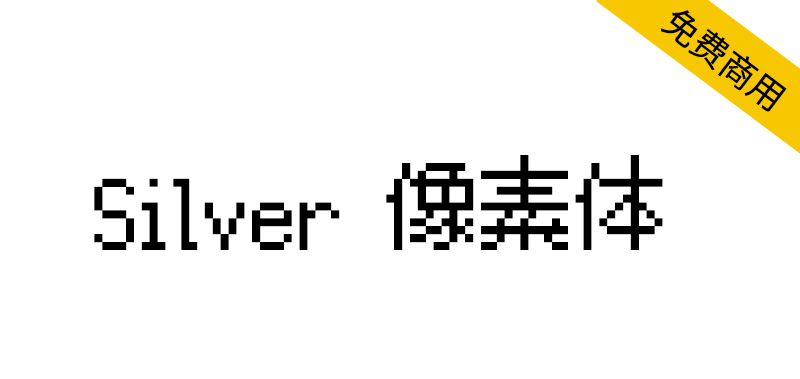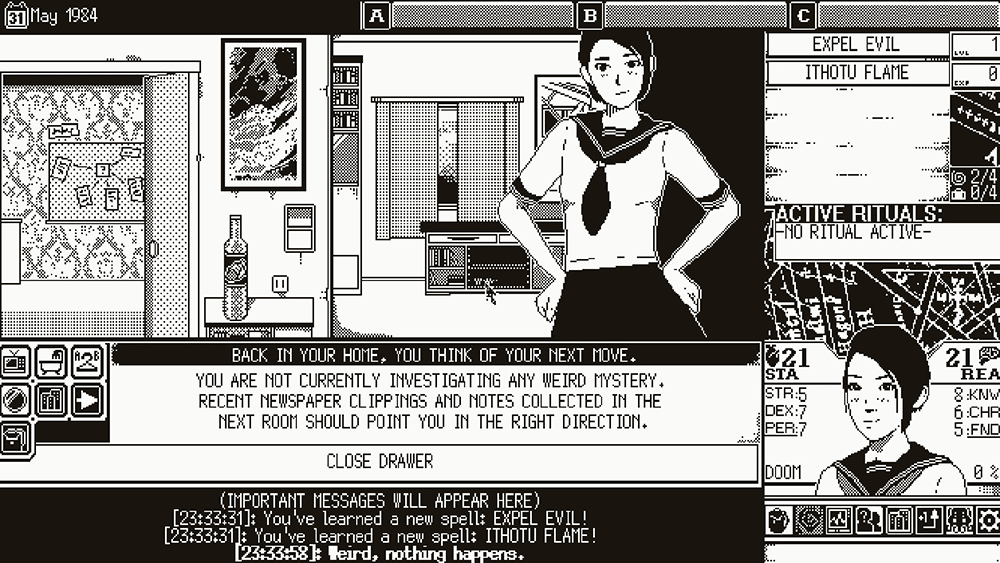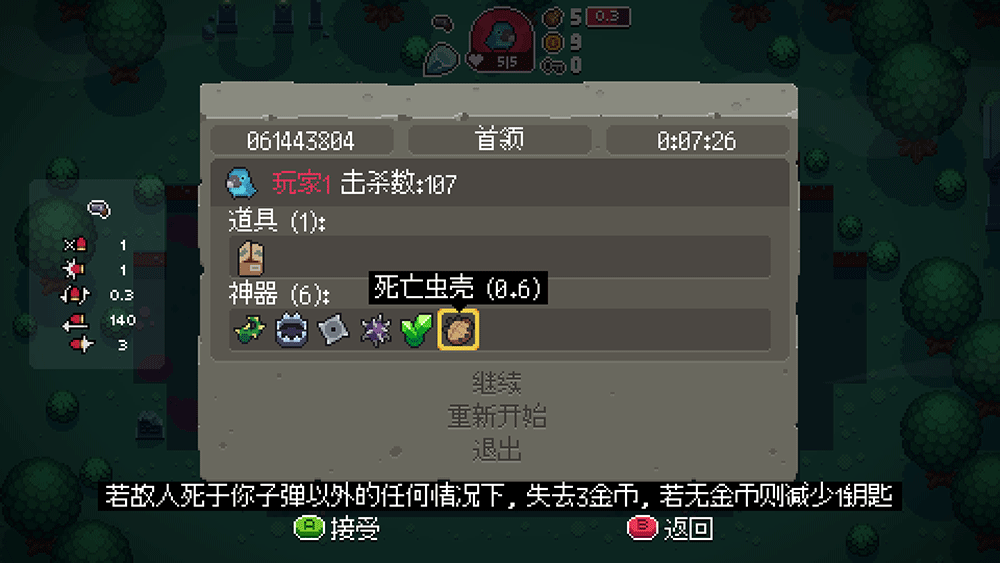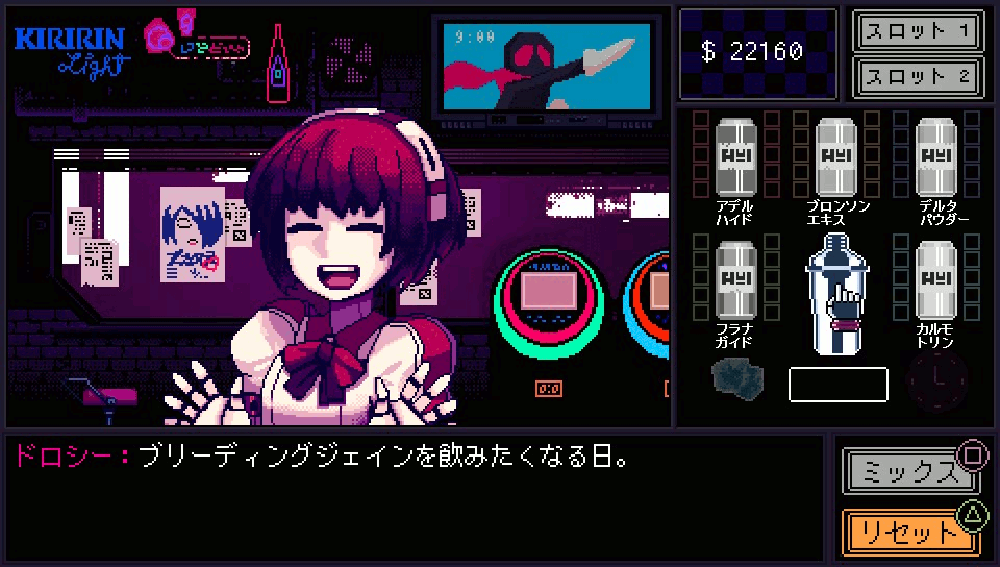
感谢您对Silver的兴趣,Silver是游戏和游戏爱好者的首选多语言像素字体。Silver在字体中内置了TRC和Lotcheck兼容的游戏板按钮,以及完整的键盘和鼠标提示!不再在文本字段上叠加图像!
这是一个正在进行的项目,将不断更新新的Unicode字形。目标是成为像素游戏和应用程序的实际字体。
免费的像素字体,适用于拉丁语、中文、韩语、日语、切罗基语、北欧文字、西里尔文和其他字符集。
Thank you for your interest in Silver, the premiere multi-language pixel font for games and game-likers. Silver has TRC and Lotcheck compliant gamepad buttons built right into the font, alongside a full keyboard and mouse prompts! No more overlaying images onto your text fields!
This is an on-going project and will be continuously updated with new Unicode Glyphs. The goal is to be the defacto font for pixel games and applications.
A free* pixel font for Latin, Chinese, Korean, Japanese, Cherokee, Runic, Cyrillic, and other character sets.